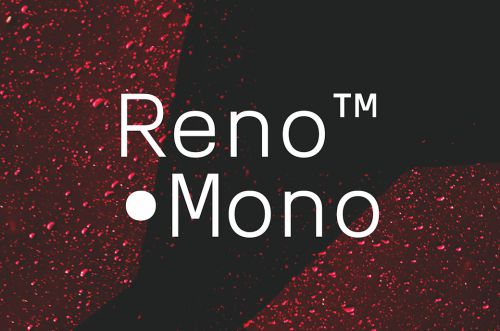
RenoMono
RenoMono 是一款等宽字体 (Monospaced Font),其名称中的“Mono”明确表明了它的核心设计理念:所有字符(包括字母、数字、符号)在水平方向上占据相同的宽度。这类字体通常专为代码编辑、终端界面、纯文本处理等场景而设计,旨在提供卓越的文本对齐和清晰的字符区分。RenoMono 结合了现代技术感与等宽字体特有的结构美学,为开发者和技术内容创作者提供了一个高效且具有独特风格的选择。